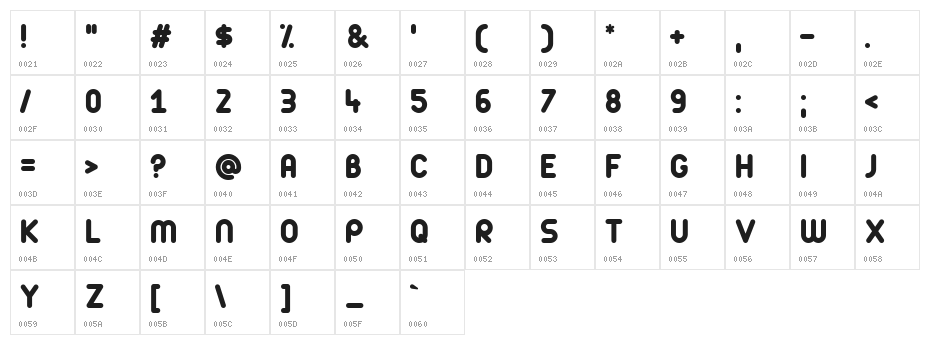
Arista Font
| Anwendungsfall | Headlines, Logos, Digital Interfaces |
| Vorgeschlagene Projekte | Ideal for branding, advertising, children's books, and digital interfaces where a friendly and modern look is desired. |